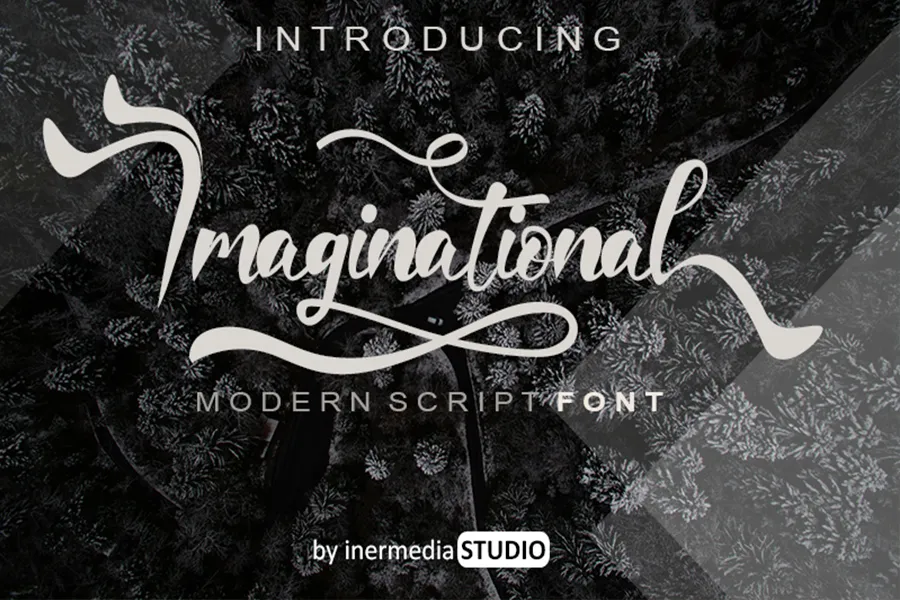
Imaginational Font é uma fonte de calligrafia que mantém a sofisticação do gênero enquanto se move para um estilo contemporâneo e fresco. Esta versatilidade faz dela uma escolha perfeita para designers apaixonados por criar ideias únicas, tanto no design de letras quanto na produção de materiais de escrita. Seja em etiquetas de papel ou títulos respeitáveis, cartões personalizados ou outros materiais de escrita, o Imaginational Font oferece uma aparição elegante e atualizada que se destaca nas mais diversas plataformas digitais. Suas linhas finas e suas formas arredondadas proporcionam um equilíbrio perfeito entre os elementos modernos e a riqueza do design tradicional, tornando-a uma fonte indispensável para designers de todo o mundo.